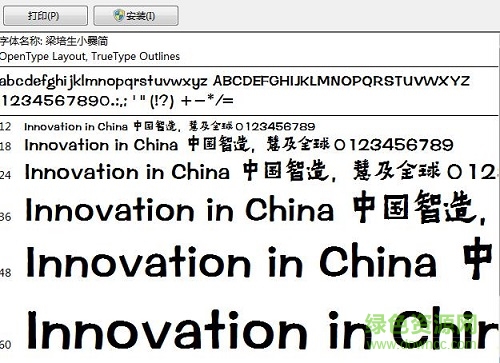
梁培生小爨簡(jiǎn)是一款根據(jù)故爨體字制作而來(lái)的電腦字體,該字體筆力雄強(qiáng),結(jié)體茂密,繼承漢碑法度,有隸書(shū)遺意,運(yùn)筆方中帶圓,筆畫沉毅雄拔,非常有特色,喜歡可以下載使用!
梁培生小爨簡(jiǎn)是一款獨(dú)具魅力的中文字體,是根據(jù)中國(guó)古代稀有字體爨體字打造的代表云南特色的字體,是中國(guó)漢字從隸書(shū)到楷書(shū)的過(guò)渡字體。